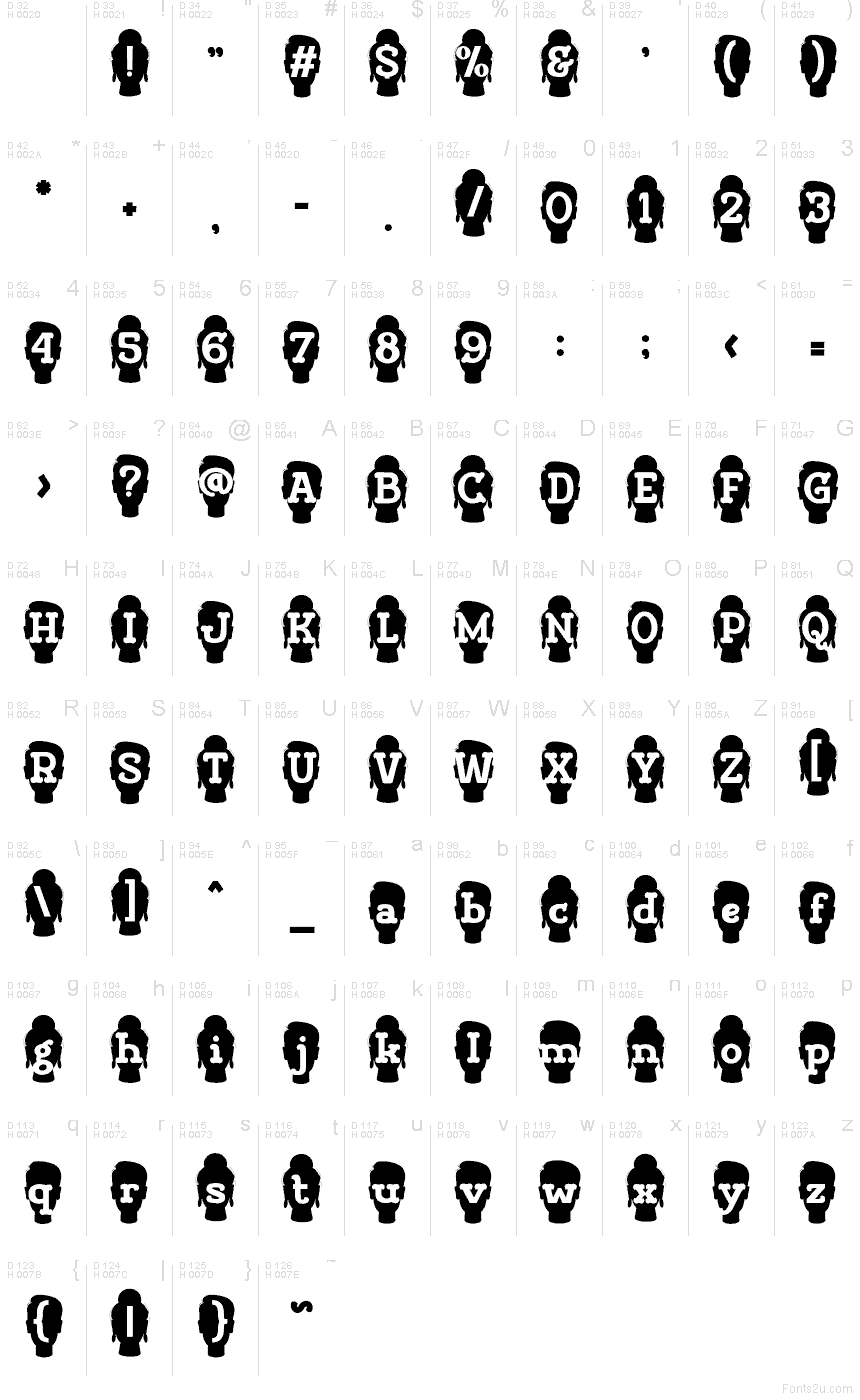
Visage Face Four
Visage Face Four aus dem Hause Putracetol Studio ist eine kostenlose Display-Schrift mit einem spielerisch-grotesken Karneval-Flair. Die Buchstaben sind in kräftige, schwarze Köpfe eingebettet – mit tropfenden Konturen und abgerundeten Kronen. Dadurch wirkt das Alphabet wie eine Reihe von Masken oder Totems, während die weißen Innenformen weich, puffy und leicht exzentrisch vor den massiven Silhouetten hervorstechen.
Diese kostenlose Schriftart eignet sich perfekt für Poster, Zine-Cover, Halloween-Flyer, Band-Merchandise und Verpackungen, bei denen das Lettering selbst zum grafischen Maskottchen werden soll. Dank ihres Charakters als individuelle kleine Figur anstelle einer neutralen Display-Form ist sie zudem ideal für kurze Überschriften und monogrammartige Initialen.